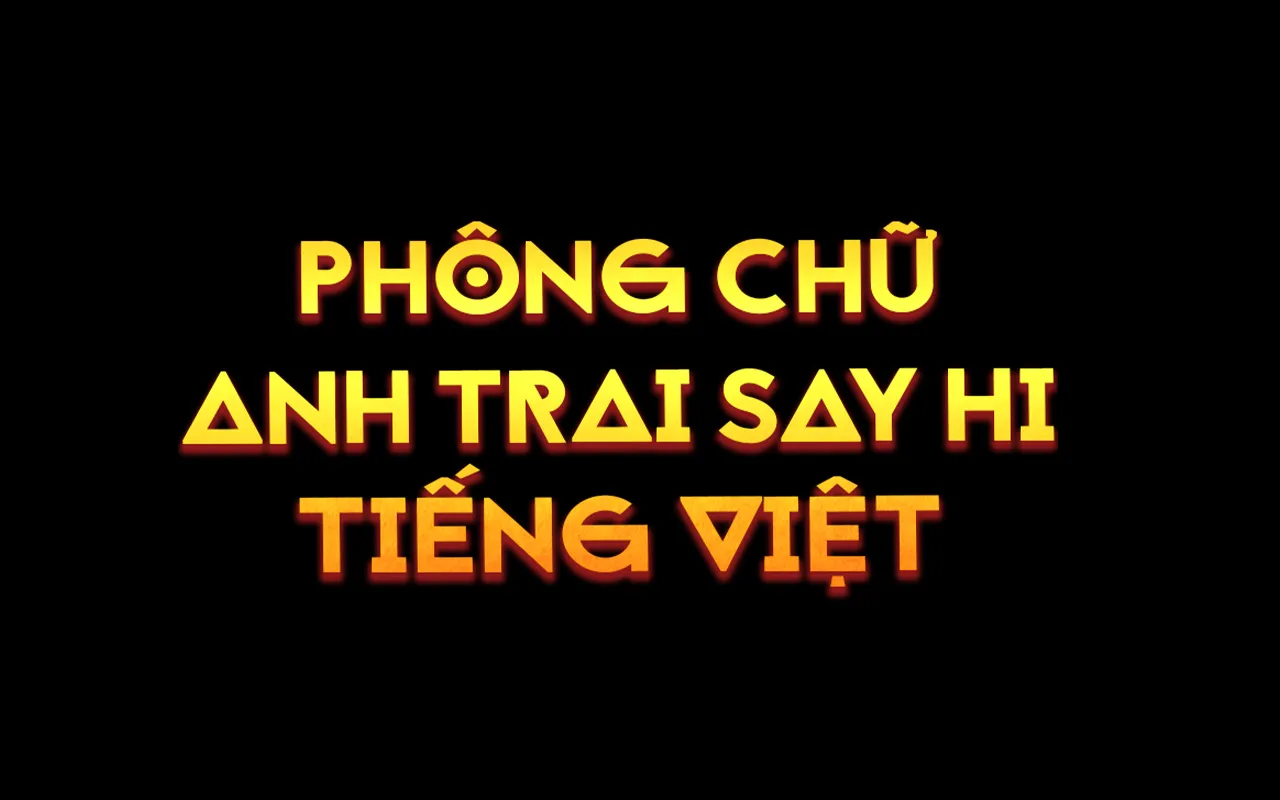
Font chữ Anh Trai Say Hi là bộ font việt hóa từ Jaapokki – một typeface sans-serif nổi tiếng với phong cách tối giản, hiện đại, phù hợp cho nhiều dự án thiết kế như tiêu đề, logo, poster, banner hay ấn phẩm truyền thông. Trong thời gian gần đây, phông chữ này trở thành tâm điểm tìm kiếm vì được sử dụng trong gameshow Anh Trai “Say Hi”, khiến nhiều designer quan tâm đến phiên bản Font Anh Trai Say Hi 2025 hỗ trợ đầy đủ phông chữ tiếng Việt.
Giới thiệu bộ Font Anh Trai Say Hi Việt hóa
Bộ font FZ Jaapokki được Việt hóa tỉ mỉ với toàn bộ dấu tiếng Việt được thiết kế lại, kerning cân chỉnh đồng bộ, đảm bảo hiển thị rõ ràng và đẹp mắt trên mọi nền tảng. Bộ này bao gồm 3 phong cách chính:
- Jaapokki Regular – Sans-serif hiện đại, tối giản, giữ form chữ gọn gàng và dễ đọc.
- Jaapokki Enhance – Phiên bản sáng tạo hơn với các điểm nhấn hình học độc đáo trên chữ in hoa.
- Jaapokki Subtract – Phong cách “cắt nét” tạo khoảng trống nghệ thuật bên trong chữ in hoa.
Font chữ Jaapokki có gì đặc biệt
Font chữ FZ Jaapokki, hay còn được biết đến với tên “Anh Trai Say Hi” khi được Việt hóa, có một số đặc điểm đặc biệt:
- Phong cách Sans-serif hiện đại: Jaapokki có thiết kế tối giản và hiện đại, phù hợp với nhiều phong cách thiết kế khác nhau.
- Điểm nhấn hình học: Các chữ in hoa có điểm nhấn hình học độc đáo, tạo hiệu ứng thị giác mạnh mẽ. Chữ thường giữ phong cách liền mạch, hài hòa với tổng thể. Số và ký tự đặc biệt được trau chuốt, đồng bộ phong cách.
- Chi tiết cách điệu tinh tế: Các chữ cái như “A”, “V”, “W” có hình tam giác cá tính, trong khi “R”, “Q”, “O”, “G”, “D” được cách điệu bởi các nét sổ chéo và ngang.
- Hỗ trợ tiếng Việt: Bộ font này đã được Việt hóa tỉ mỉ với toàn bộ dấu tiếng Việt được thiết kế lại và kerning cân chỉnh đồng bộ.
- Đa dạng phong cách: Bộ font gồm 3 phong cách chính: Jaapokki Regular, Jaapokki Enhance và Jaapokki Subtract, mỗi phong cách mang đến một cảm giác riêng cho thiết kế.
Tóm lại, font chữ Jaapokki là lựa chọn hoàn hảo cho các dự án thiết kế cần sự hiện đại, tinh tế và nổi bật. Đây là lựa chọn hoàn hảo cho thiết kế logo, thương hiệu, bao bì sản phẩm, poster hay các ấn phẩm quảng bá cần sự hiện đại và nổi bật.
Ứng dụng của Font chữ Anh Trai Say Hi
Với độ rộng nét đồng đều, bố cục cân đối và khả năng hỗ trợ phông chữ tiếng Việt hoàn chỉnh, bộ font việt hóa này đáp ứng tốt cho:
- Thiết kế nhận diện thương hiệu (logo, slogan, bộ nhận diện).
- Ấn phẩm truyền thông (poster, banner, infographic).
- Thiết kế kỹ thuật số (website, UI/UX, app).
- Dự án sáng tạo cá nhân (artwork, typography art).
Font chữ Anh Trai Say Hi Việt hóa không chỉ đẹp và hiện đại, mà còn giữ nguyên tinh thần tối giản, sáng tạo của bản gốc FZ Jaapokki, đồng thời hỗ trợ đầy đủ phông chữ tiếng Việt. Đây là bộ font việt hóa lý tưởng cho mọi designer muốn nâng tầm thiết kế trong năm 2025.